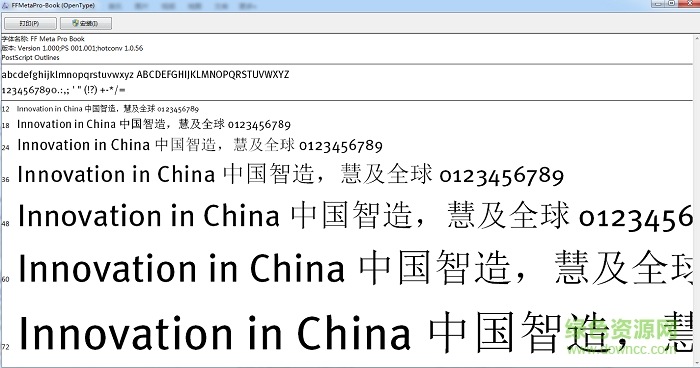
ff meta字體是本站為廣大字體愛(ài)好者整理的字體包,包含了bold and book等多款字體,字形優(yōu)雅,大方現(xiàn)代,易讀性強(qiáng),需要的朋友快來(lái)下載吧!
最適合的正文字體應(yīng)該是近似“半透明的”。一方面采用適當(dāng)?shù)囊r線技巧,以提高字體在不同字號(hào)和各種閱讀環(huán)境下的識(shí)別率。另一方面在字形結(jié)構(gòu)上應(yīng)該采用和宋體和黑體近似的字形結(jié)構(gòu),因?yàn)檫@種熟悉的字形,會(huì)降低識(shí)別的難度,也就是盡量不讓人注意到字體本身,而是文字背后的含義。